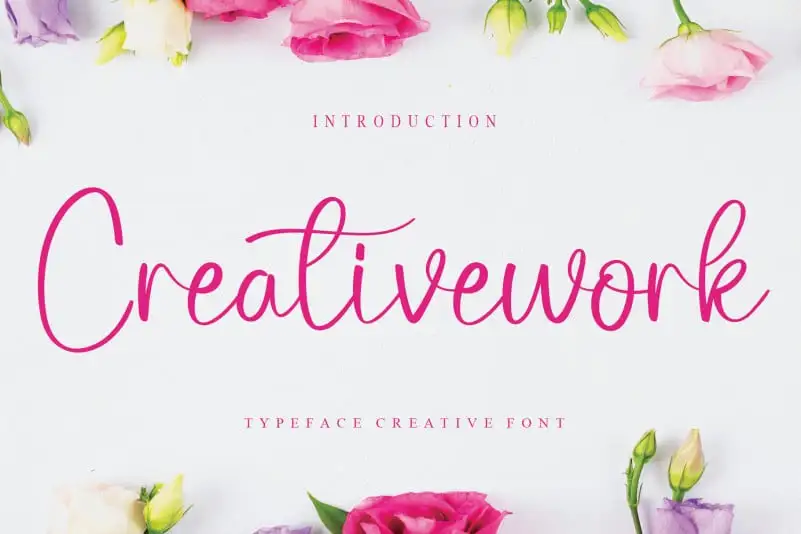
Creativework Calligraphy Font – Fonte Grátis
Creativework Calligraphy Font
Descubra a beleza única das Calligrafias Manuscritas com “Creativework Calligraphy Font”, uma fonte criada pelo Designer creativeletter. Seja você um designer, artista ou simplesmente alguém que aprecia a arte do texto em seu formato mais autêntico e expressivo. Com sua interface fluida e detalhes de alta qualidade, esta fonte permite que você adquira experiências únicas, tanto para projetos profissionais quanto pessoais. Apenas um clique e transforme qualquer projeto em uma obra de arte inovadora, oferecendo você a oportunidade de explorar novos horizontes no design de texto. Não perca mais tempo buscando fontes adequadas, tente agora “Creativework Calligraphy Font” da creativeletter para adicionar personalidade e originalidade à sua próxima criação visual.